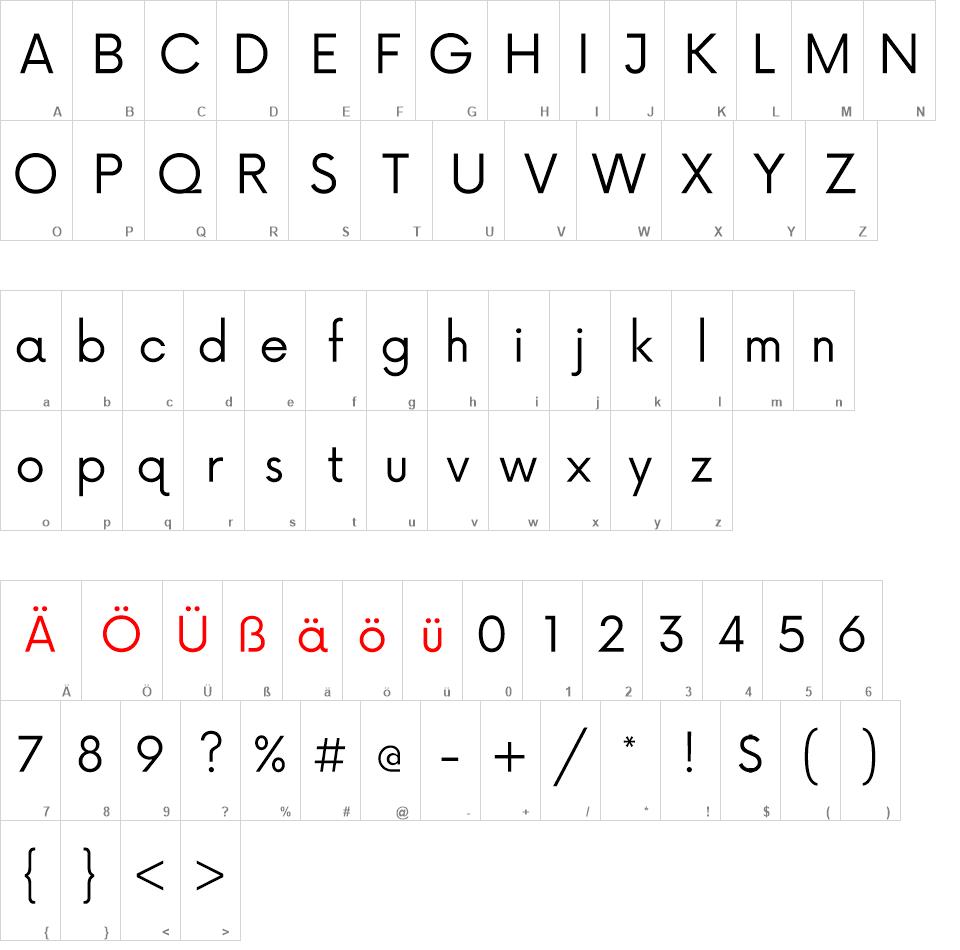
Now
Now  font
Jetzt Subtype ist eine einfache geometrische Form von Alfredo Marco Pradil. Jetzt ist das Font-Format Open Source. Jetzt ist Alt eine alternative Version des Textformats. Der einzige Unterschied ist das kleine "a".